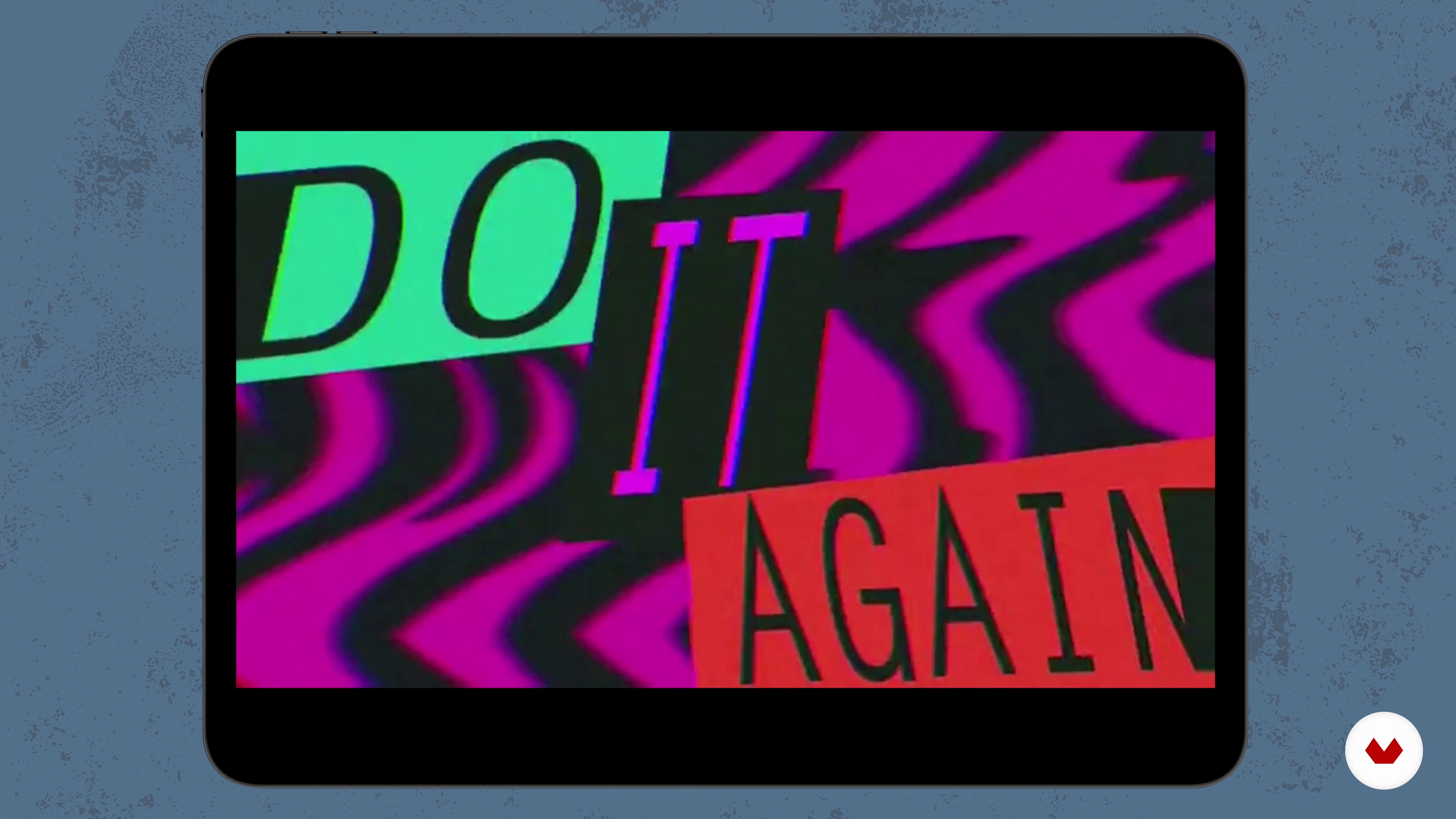
Typographie expressive en mouvement avec After Effects
Composition et organisation du lettrage
À propos de la leçon : Composition et organisation du lettrage
“Commençons par explorer comment notre phrase sélectionnée peut s'asseoir, s'aligner et être composée. À l'aide de croquis approximatifs et lâches et de quelques stylos brillants, nous déterminerons la meilleure façon d'aligner nos lettres. Nous réfléchirons également à la manière d'étendre notre travail pour qu'il devienne quelque chose de plus lorsqu'il sera finalement animé.”
Dans cette leçon, Mat Voyce aborde le sujet : Composition et organisation du lettrage, qui fait partie du cours Domestika en ligne : Typographie expressive en mouvement avec After Effects. Apprenez à créer des lettres aux formes pleines de personnalité et à leur donner vie de façon ludique grâce à l'animation.
“Composition et organisation du lettrage Maintenant, il est temps d'obtenir des stylos, du papier, et de planifier à la fois notre composition initiale et finale. Dans cette leçon, je vais vous aider à esquisser une idée approximative de votre phrase, en utilisant tous les points de référence des leçons précédentes, et nous planifierons la composition et la superposition de la façon dont toutes les lettres se développent à la fin. Cela va nous aider à pré-planifier l'étape d'animation, ce qui sera utile et accélérez à la fois le temps et le flux de travail de la façon dont nous créons cette ...”